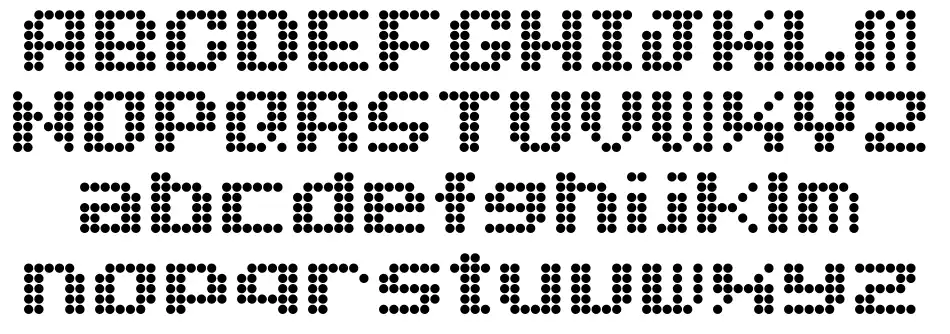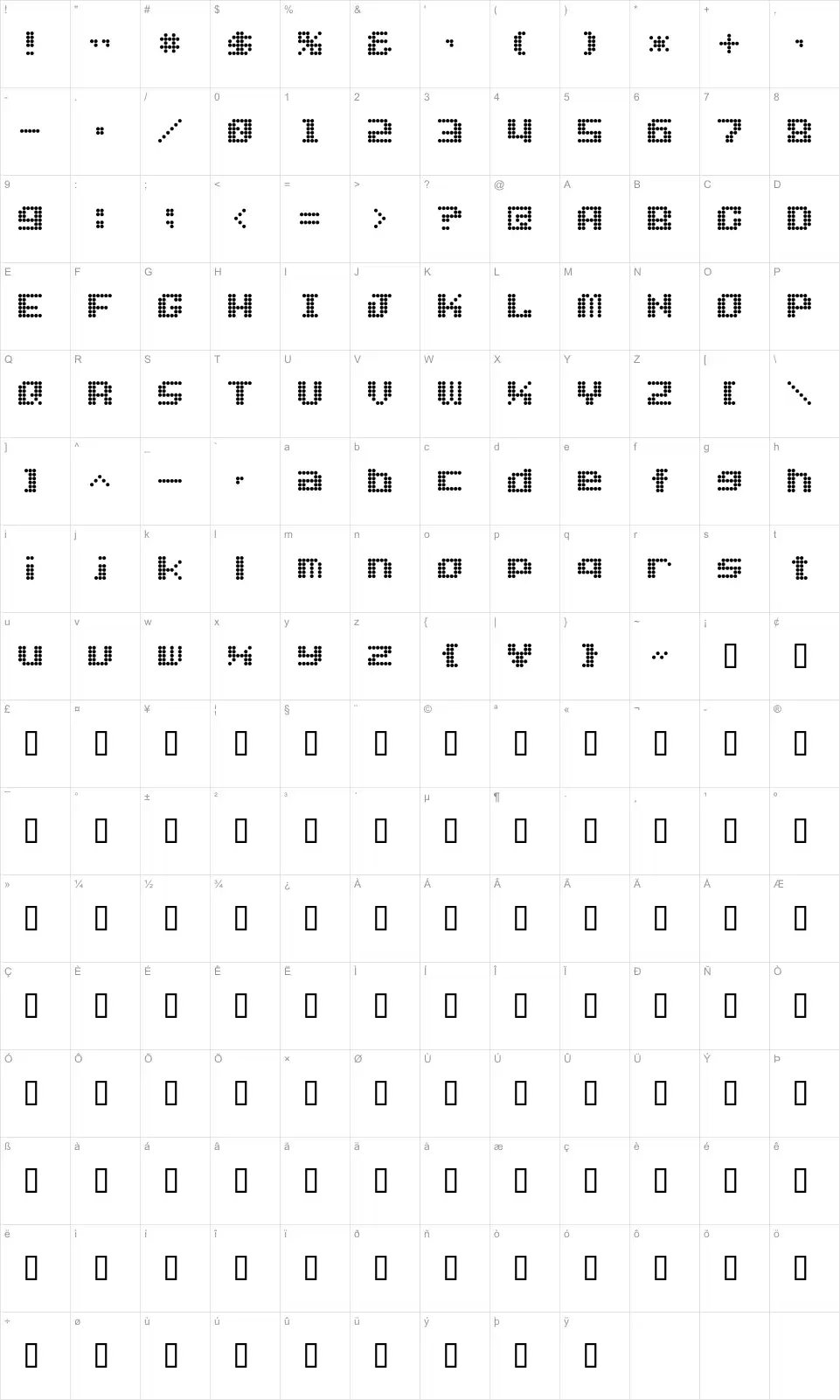
A Dot Font é uma fonte tecnológica criada pelo designer Eisuke Furukawa, ideal para adicionar um toque moderno e futurista a seu design. Esta tecnológica e minimalista fonte LCD é perfeita para ambientes de tecnologia, mídias digitais ou mesmo elementos gráficos de alta tecnologia. Se você está procurando pela Dot Font, agora pode facilmente obtê-la ou gerar um preview personalizado de texto para ver como ela se destaca. Esta fonte está licenciada sob uma modalidade de software compartilhado, o que a torna acessível para projetos de todos os tamanhos. Com um tamanho de apenas 6 KB, ela é uma opção leve e rápida de ser usada em qualquer projeto digital. Desde sua adição em 12 de julho de 2022, muitos designers já tiveram a chance de experimentar o visual único desta tecnológica fonte. Visite o site do designer, www.hyperiongraphics.com, para explorar mais opções de fontes.
Designer: Eisuke Furukawa